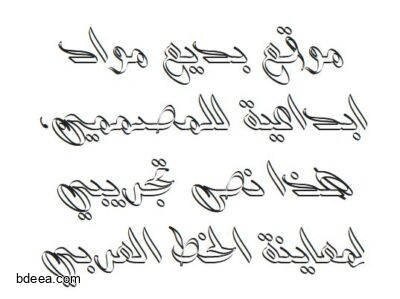
تحميل خط ايمن19 عربي ayman19 arabic font ttf خط جديد للاستخدام في النصوص العربية المميزة يضيف النصوص الى التصاميم العربية والمطبوعات والعروض التقديمية بالكلمات العربية والارقام بشكل مميز يمكنك تثبيته على جهازك والبدء باستخدامه في برامج التصميم
يتميز بالخط بالمرونة والخفة والشكل الانيق في الكتابة والحروف يمكن معاينته وتجربة استخدامه ليضيف لك تميز الى تصاميمك